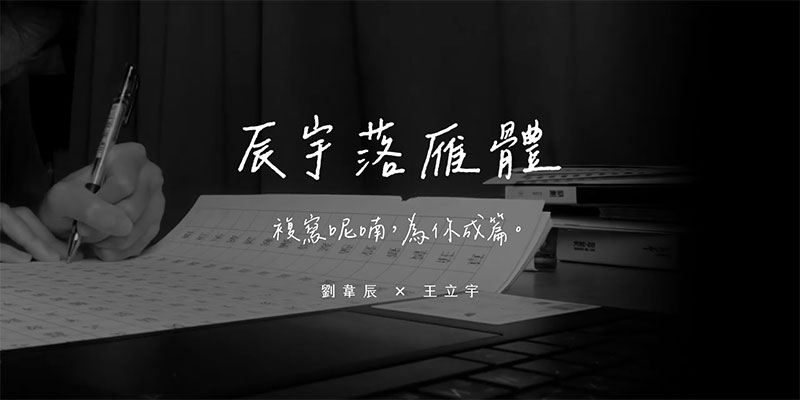
「辰宇落雁體」是我與韋辰在學校的自主學習計畫,由韋辰負責書寫,我進行後製而成。手寫字型就像是我們將字詞複寫於紙上,讓字跡留下,以這種近似雋永的形式封裝,使被複寫的日常沒有保質期,也像是一種永恆的召喚,在任何無法抵達的以後,都能為你書寫成篇。
制作故事
唉,你要不要做手写字体?
去年的八月,那阵子我开始关注字体相关议题,在一次偶然看到韦辰的手写字后,萌生出要是自己也能做一套手写字体,真是太酷了!而适逢108课纲的我们,课纲强调自主学习的精神,正巧让我们有机会发展计划,于是,手写字体的钻研之路就这样开始了⋯⋯
但「万事起头难」,我们一开始的起步并不这么顺利,对于字体不太熟悉的我们于是开始搜寻相关资讯,忽而地想到,YouTube频道「壹加壹」与justfont推出的粒线体,我们写信请教手写字体的前期制作方向,获得了他们真诚的回复,他们向我们分享制作字体需注意的要点,也在计划过程中提供我们咨询与技术指导,成为很大的助力。
我们最初是在线上字体制作平台──「守写字网站」习得手写字体的制作流程,后来为了更大程度的制作自由,我们尝试拆解流程,并以自己的方式进行制作,然摸索的过程并非一蹴可及,在那段期间的每周四,我潜心钻研的同时,韦辰就在一旁书写,两个人窝在图书馆的角落为心中的理想并肩努力着,制作字体是枯燥的,日复一日的书写、修改与后制,现在想想,我们还挺浪漫的,为了完成理想,不惜代价的绕了点路,也有好几次泄气的想着,或许真的做不出来了,是对于成果的想像才让我们坚持下来。
在字体做出成果后,也陆续获得不少称赞,神奇的是,制作过程中并未觉得特别的我们,在第一次打出完整的句子时,却被感动了。若浪漫一点来说,制作手写字体这件事,似将字词复写于纸上,将字迹留下为人使用。
回想制作的契机,那句「唉,你要不要做手写字体?」在今天终于实现了,韦辰写下这些文字后也将与十六岁告别,正所谓字如其人,期望她未来回首,能在字里行间看见自己。
其他可能
其实,我们在计划一开始制作的字体是以Pentel Touch书写的粗体字,但因为制作目标与后期调整较为复杂,在稿纸书写完成后,迟迟未能释出字体。而我们随后也制作了原子笔书写的版本,也就是现在的「辰宇落雁体Thin」。
上图为Pentel Touch版本字样,预计于2023年开始制作。